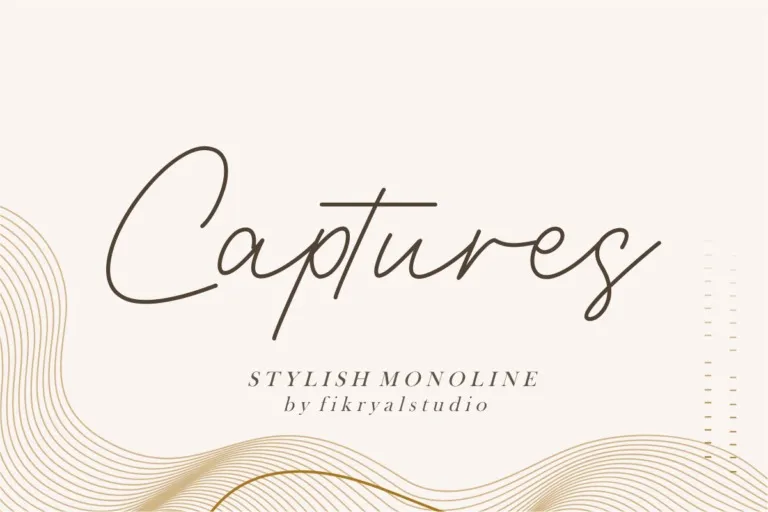
Captures Font – Fonte Grátis
Captures Font
A ‘Captures Font’ é uma elegante tipografia círula escrita a mão que traz alfabeto maiúsculo e minúsculo, números, pontuação, símbolos e caracteres diversos. Ela se apresenta como um fonte monolinha perfeita para qualquer projeto gráfico que exigir uma aparência sofisticada e arrojada. Especialmente indicado para criações de arte, marcas, convites, estaçãoários, designs de casamento, posts nas redes sociais, anúncios, embalagens de produtos, designs dos produtos, selos, fotografia ou marca d’água para eventos especiais. Esta fonte singular se encaixa perfeitamente em uma ampla gama de propósitos gráficos, tornando-a o elemento ideal para aqueles buscando estilizar seus projetos digitais e físicos com elegância e sofisticação.